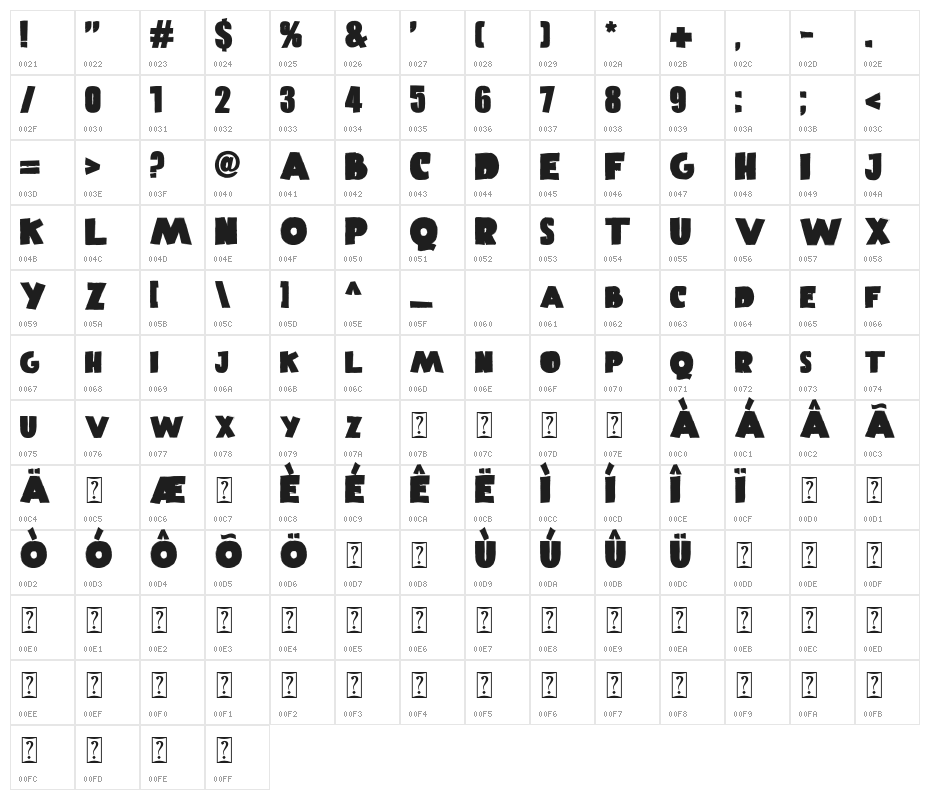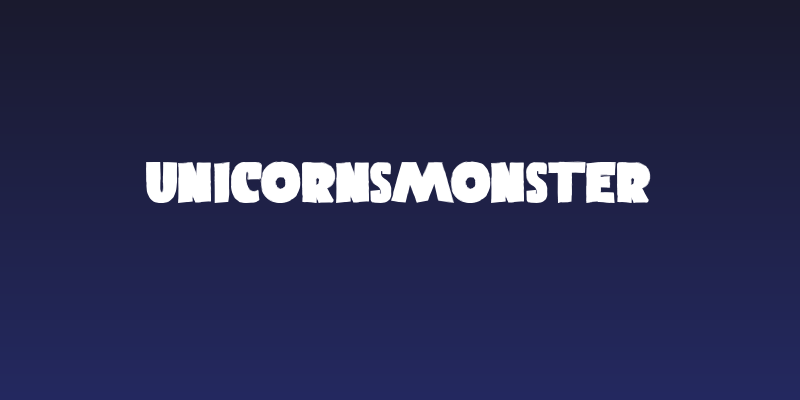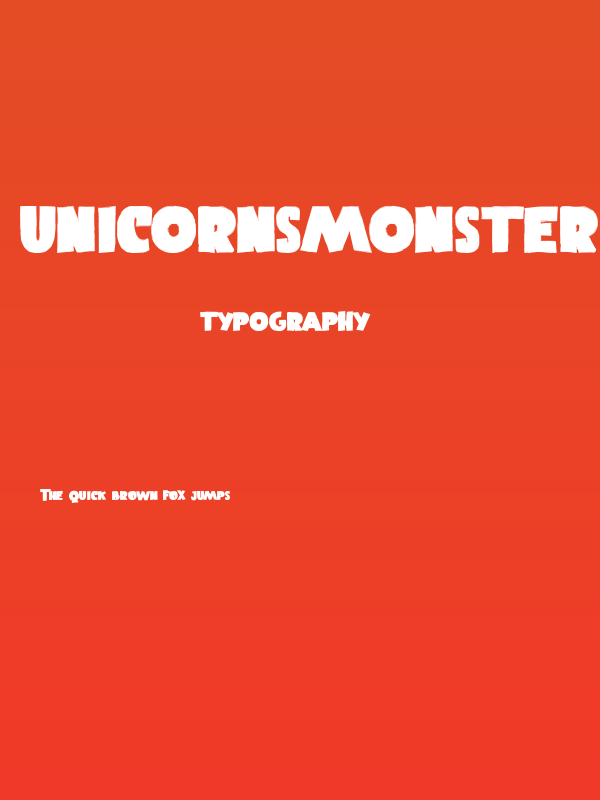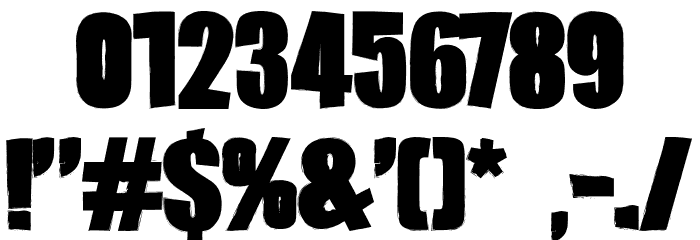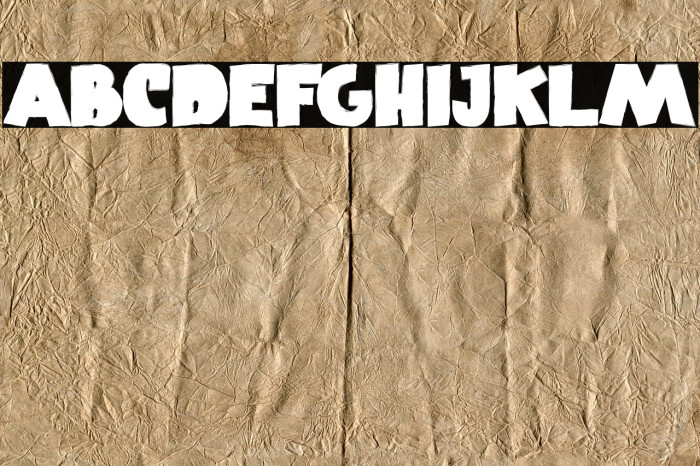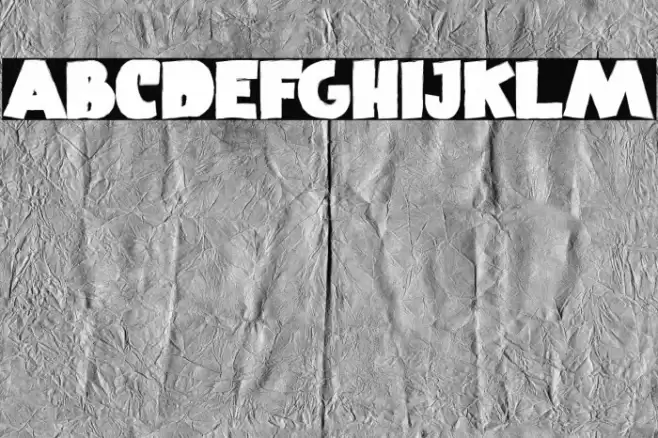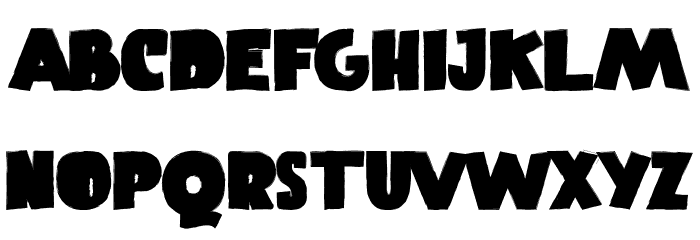
UnicornsMonster Font
Fonts by Jujun Junaedi
| Proyectos propuestos | Ideal for children's book covers, playful branding, event posters, and creative social media graphics. |